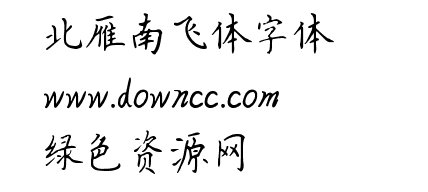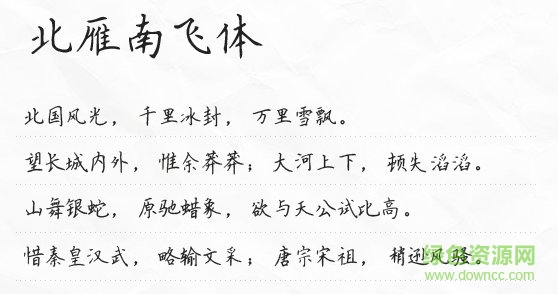
北雁南飛體是一款孤獨(dú)雅致的手寫(xiě)字體,與思雨字體庫(kù)風(fēng)格類(lèi)似,但字里行間更顯端方正直之氣,來(lái)綠色資源網(wǎng)試試吧!
有人說(shuō),愛(ài)上北雁南飛,可以用“一見(jiàn)如故”來(lái)形容,“故”是因?yàn)槟阍谶@里——你可以傾聽(tīng)到“家”的聲音;尋覓到“家”的情愫;感受到“家”的氛圍;咀嚼到“家”的滋味?!毖隳巷w體。
本字體是在國(guó)家標(biāo)準(zhǔn)簡(jiǎn)體字庫(kù)GB2312所包含6763漢字的基礎(chǔ)上,又增加了近200常用字,已經(jīng)覆蓋了大陸99.75%的漢字使用頻率,足以滿足日常需求。
思雨字體庫(kù)的字體都是以硬筆書(shū)法為主,每位作者的風(fēng)格均不想死,但都是獨(dú)居個(gè)性魅力的手寫(xiě)體,在感官上更易被讀者接受,用作手機(jī)字體更為合適。